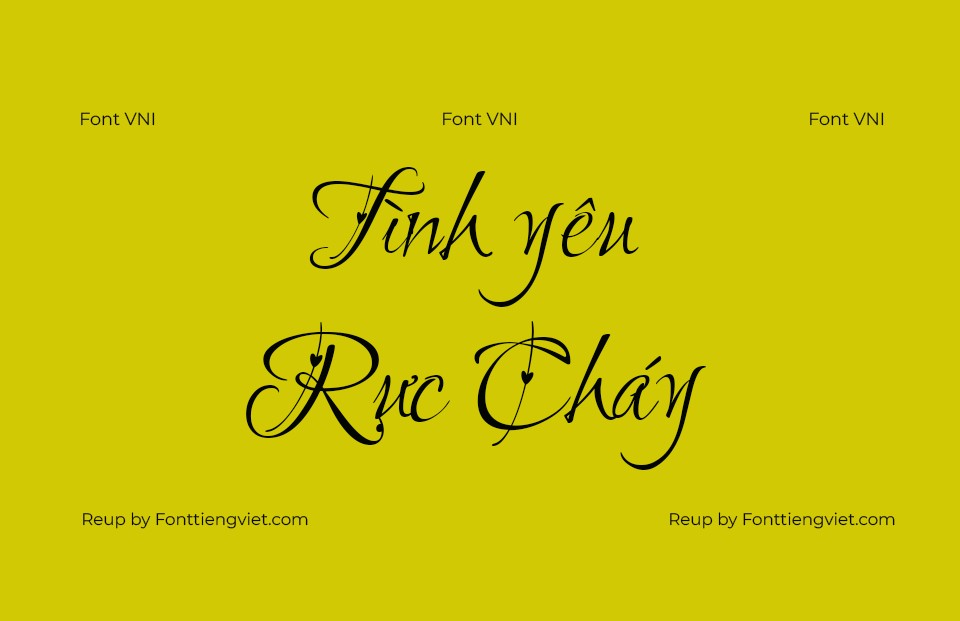
Font Việt hoá VNI 24 Love
Giới thiệu về Font Việt hoá VNI 24 Love
Trong thế giới thiết kế đồ họa, việc lựa chọn một Font Miễn Phí phù hợp đóng vai trò quan trọng để truyền tải thông điệp cảm xúc. Font Việt hoá VNI 24 Love là một trong những bộ phông chữ tiêu biểu dành riêng cho các chủ đề về tình yêu, sự nhẹ nhàng và tinh tế. Với những đường nét uốn lượn mềm mại, bộ font này mô phỏng nét chữ viết tay điệu đà, giúp các tác phẩm trở nên bay bổng và có chiều sâu hơn. Đối với các bạn học sinh hay thầy cô giáo, đây là lựa chọn tuyệt vời để trang trí thiệp chúc mừng, làm báo tường hoặc thiết kế các slide trình chiếu bài giảng thêm phần sinh động và bắt mắt.
Đặc điểm nổi bật của Font Việt hoá VNI 24 Love
Điểm khác biệt lớn nhất của Font Việt hoá VNI 24 Love chính là sự kết hợp hài hòa giữa phong cách cổ điển và hiện đại. Các ký tự được chăm chút tỉ mỉ, đảm bảo hiển thị rõ ràng ngay cả khi sử dụng ở kích thước nhỏ. Đặc biệt, bản Việt hóa này đã khắc phục hoàn toàn lỗi gõ dấu tiếng Việt, giúp người dùng dễ dàng soạn thảo văn bản trên các phần mềm phổ biến như Microsoft Word, PowerPoint hay Photoshop mà không gặp trở ngại về định dạng.
Cách sử dụng và ứng dụng thực tế
Để sử dụng hiệu quả, bạn nên kết hợp font chữ này với các tông màu pastel hoặc màu đỏ thắm để làm nổi bật chủ đề tình yêu. Nó thường được ứng dụng trong thiết kế bìa sách, menu nhà hàng hay các tiêu đề trang trí nghệ thuật. Việc cài đặt cũng rất đơn giản, chỉ cần tải về và sao chép vào thư mục Fonts trên máy tính là bạn có thể bắt đầu sáng tạo ngay lập tức.